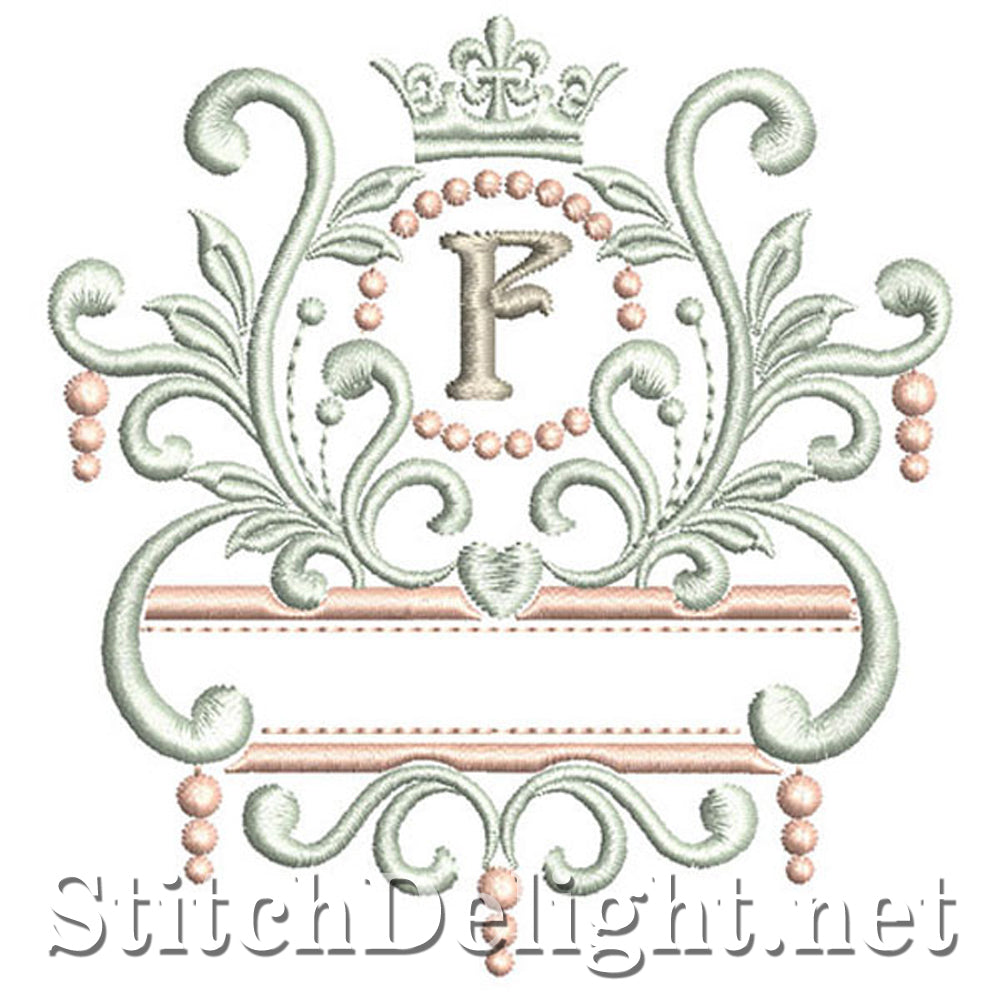
Personnalisez votre projet avec cet ensemble de monogrammes élégants (tailles de cercle 4x4 et 5x7 incluses ainsi que la version BX pour le logiciel Embrilliance - vous pouvez ajouter le nom correspondant à l'initiale comme on le voit sur la photo en utilisant SDS1194 (Tiny Arial Font) p>